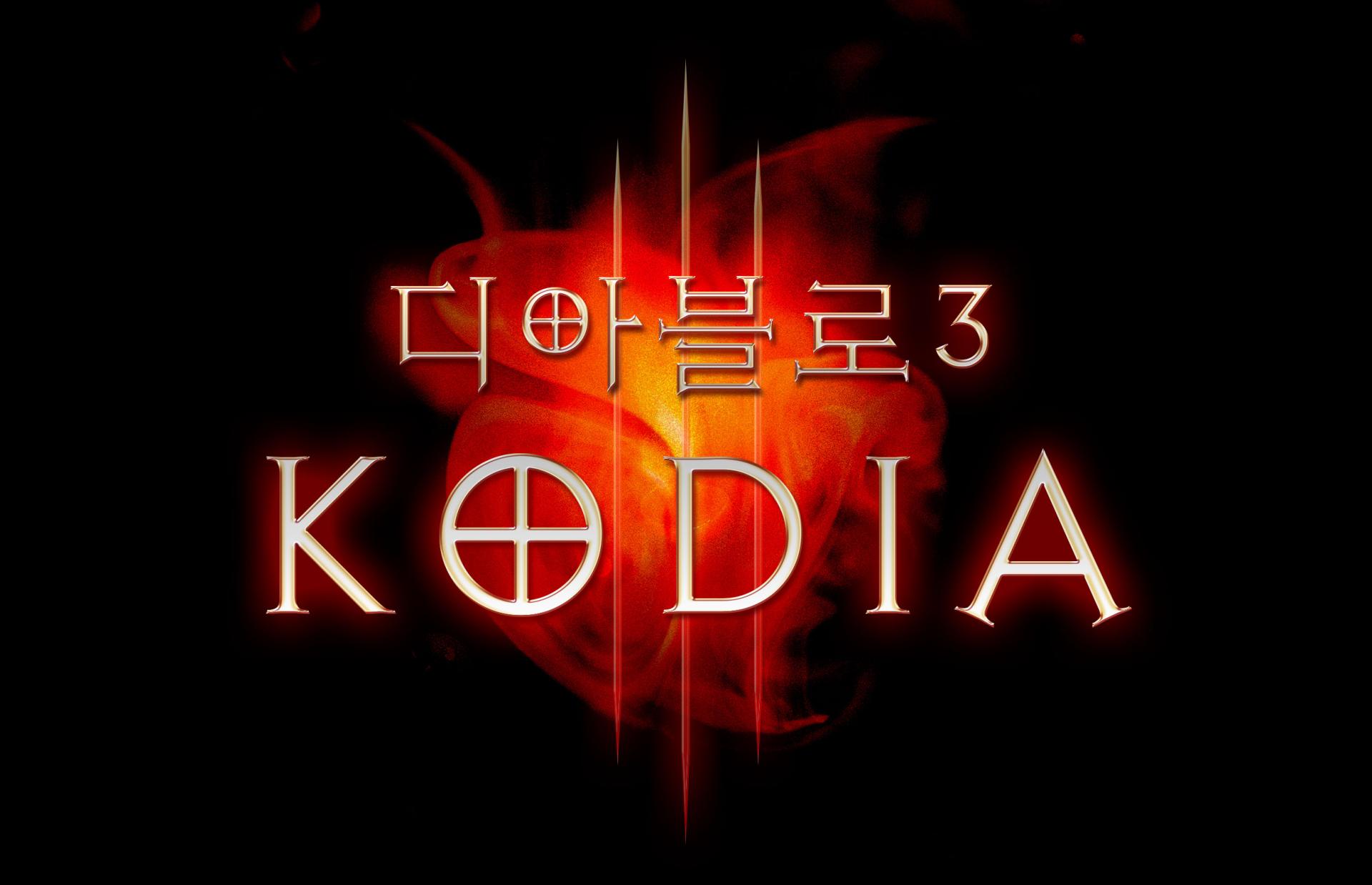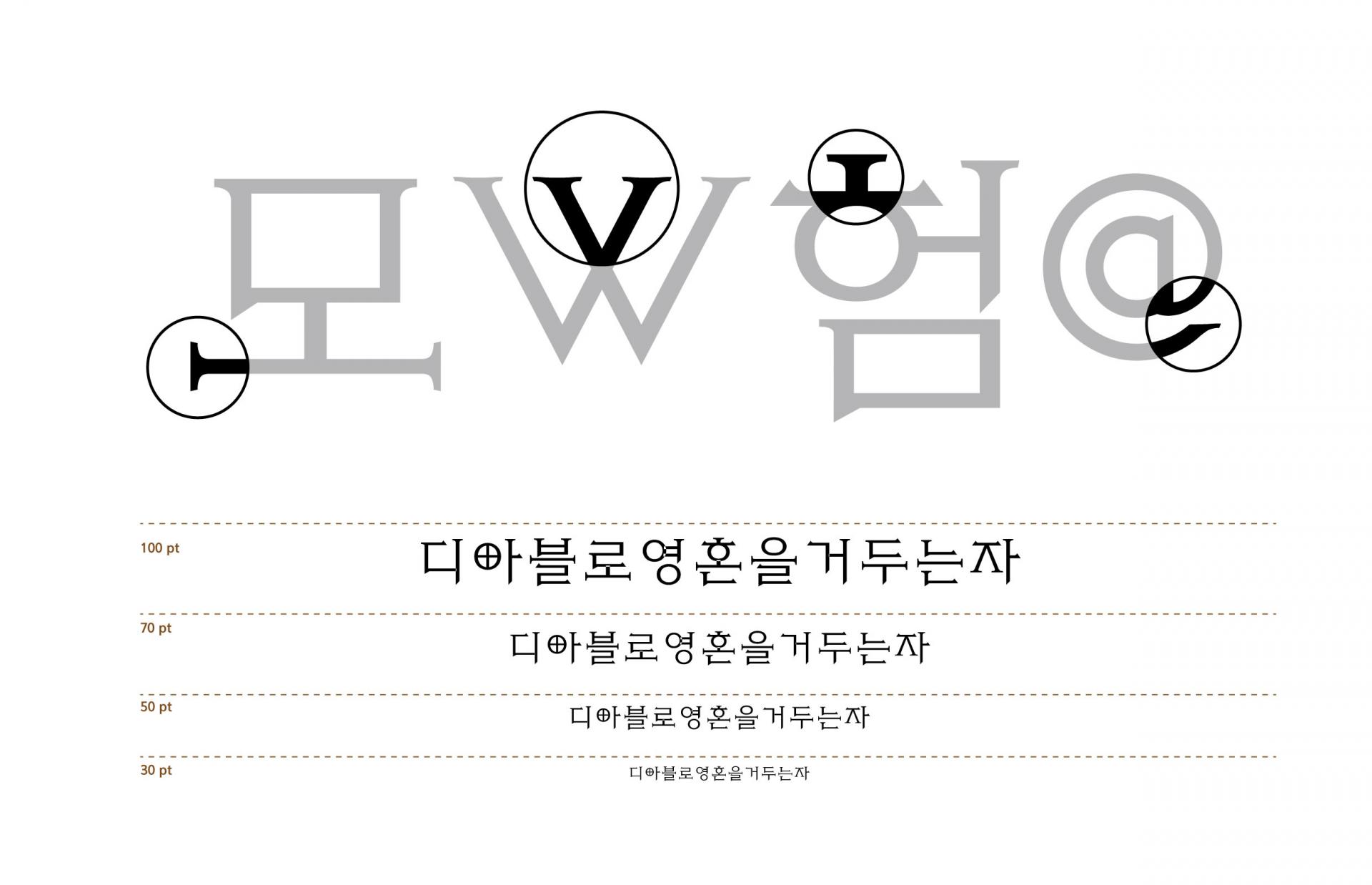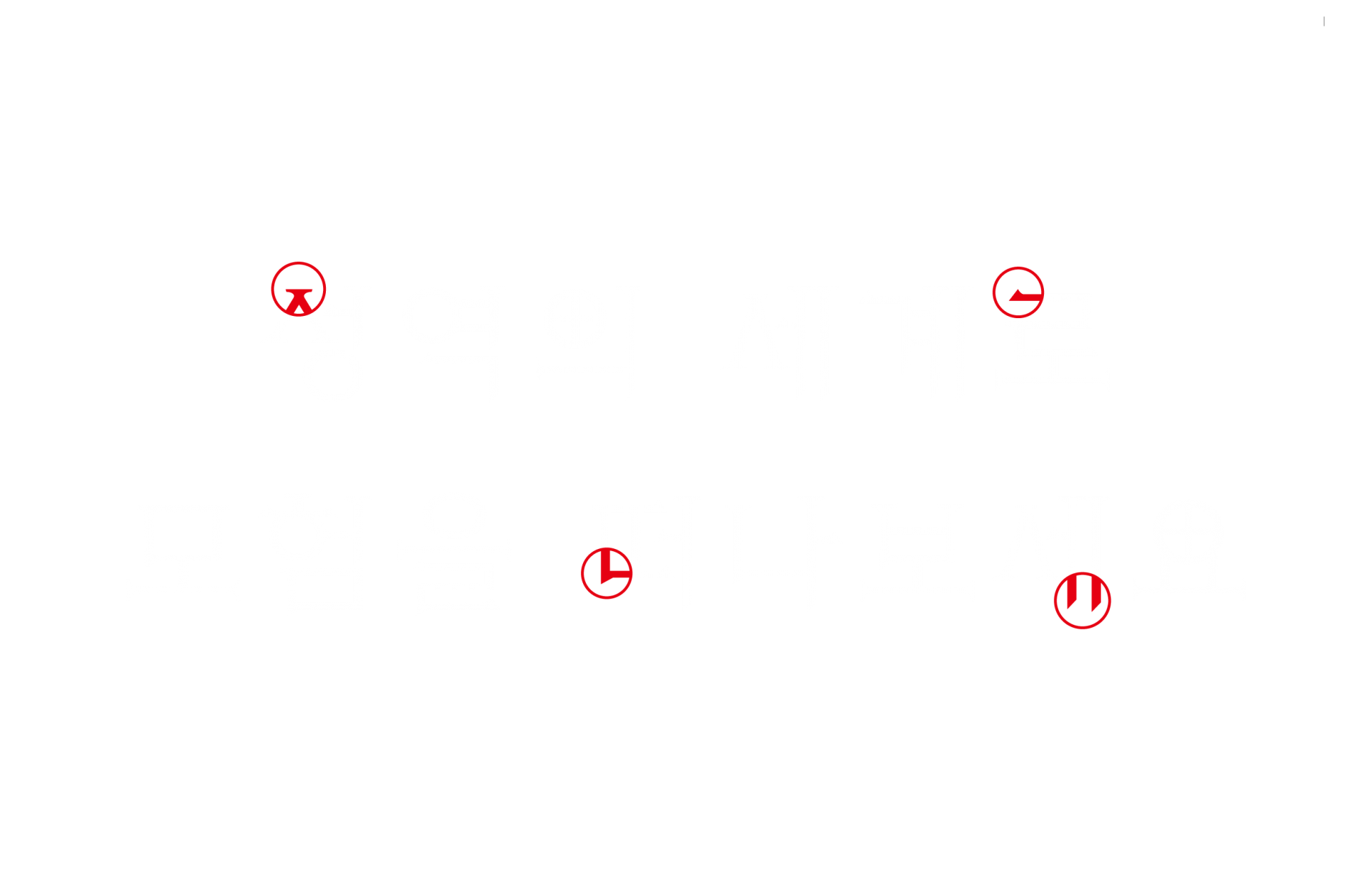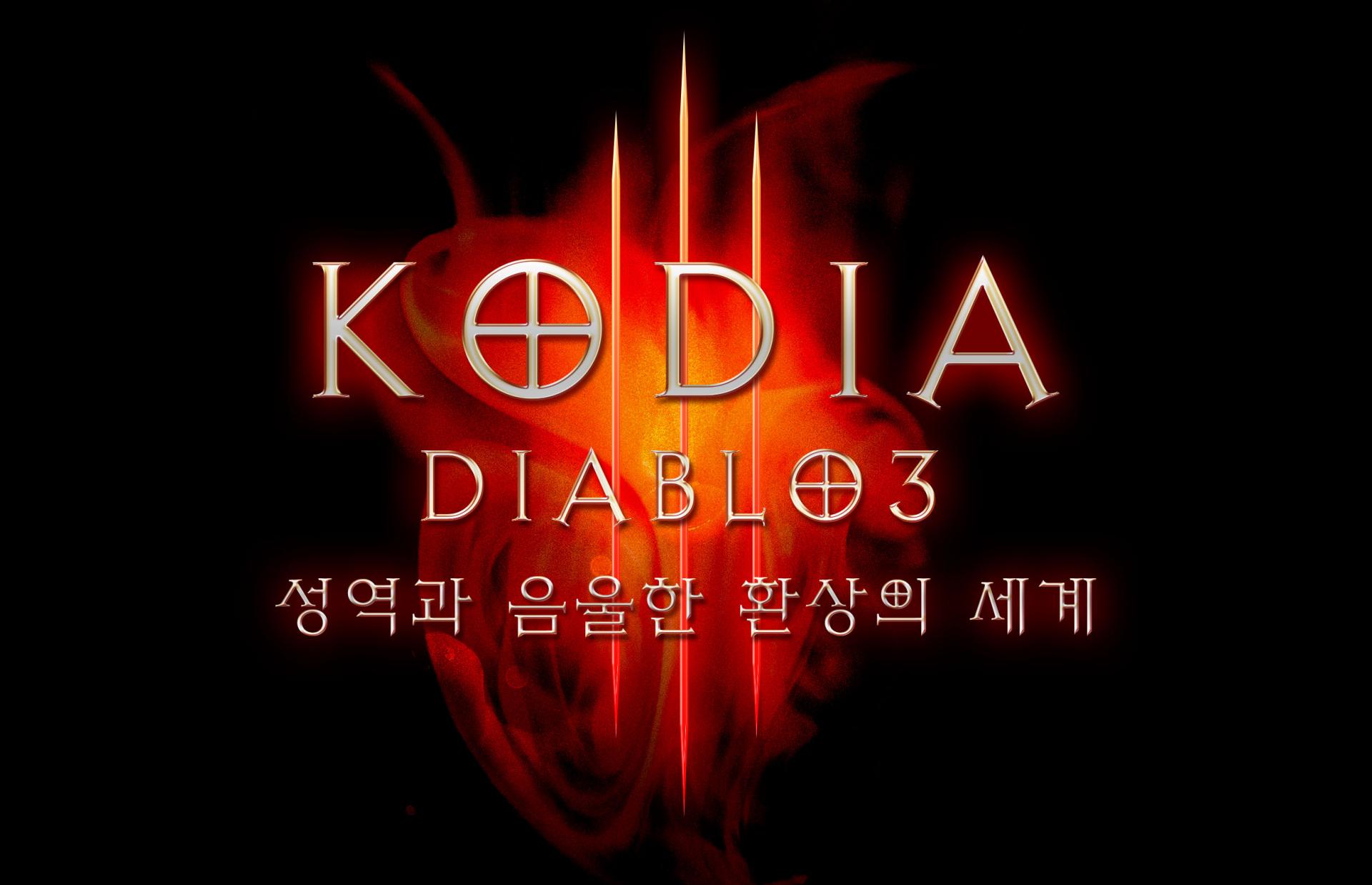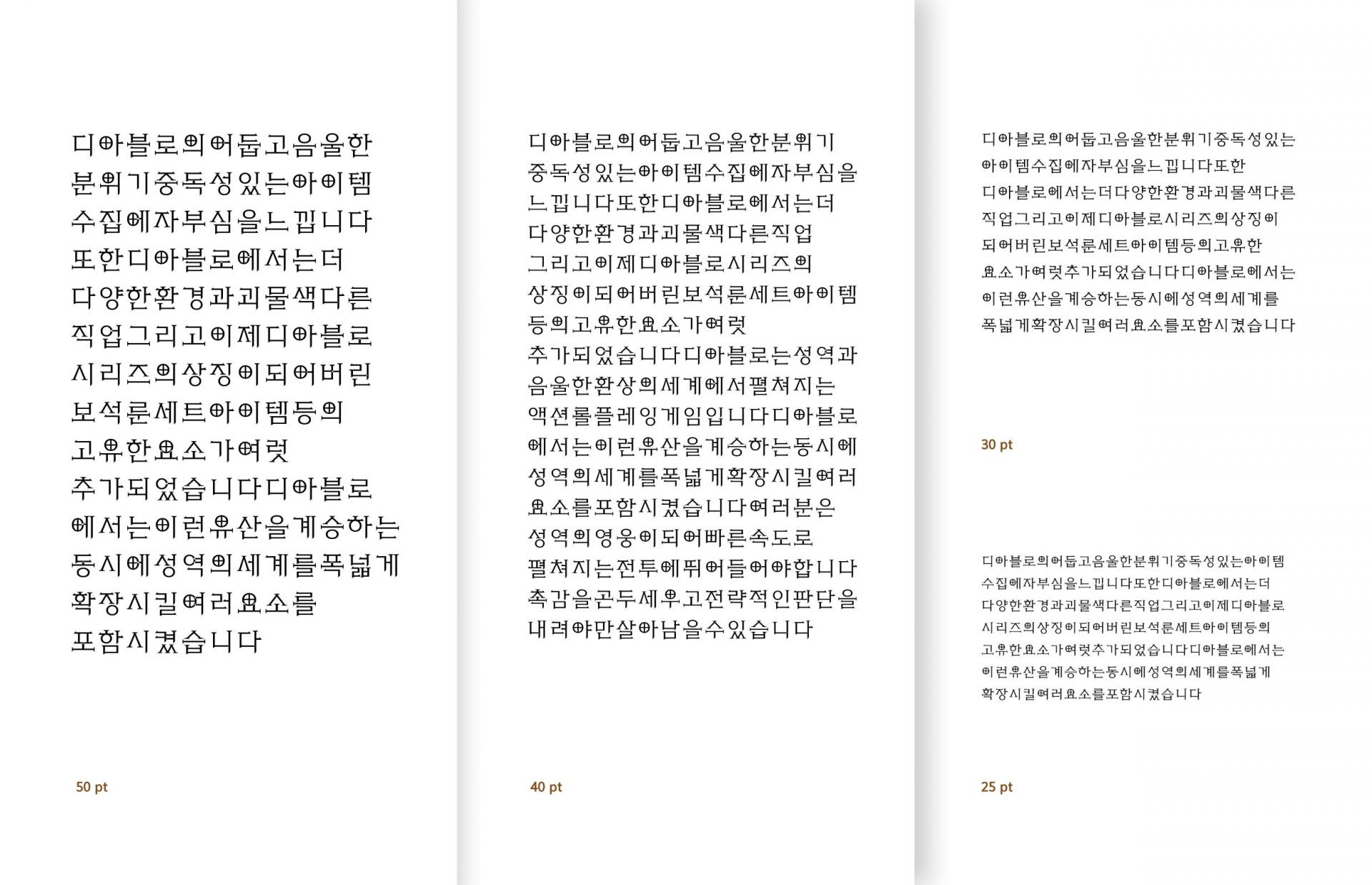
블리자드 엔터테인먼트 [KODIA]
블리자드 엔터테인먼트의 게임 '디아블로III'의 전용서체로 자사가 개발(2010-2014)하였던 전용서체 [KODIA]를 확장개발(한글 11,172자 확장)하였다. [KODIA]는 '디아블로III'의 전용서체로 사용한 서체 [Exocet]의 인상을 고스란히 한글에 이식하는 것을 목표로 하였다.